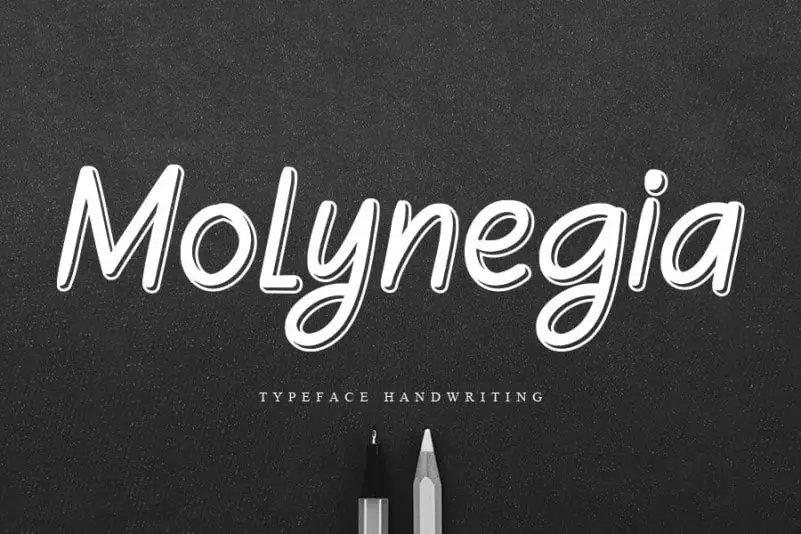
A Molynegia Handwritten Font é uma opção criativa e encantadora para aqueles que buscam um estilo autêntico e elegante na sua designação de texto. Com seu charme natural, essa fonte escrita a mão se destaca em várias aplicações, desde estilos de wall displays até embalagens exclusivas ou cartões de visita. Suas linhas suaves e gestos fluidos fazem-a perfeita para dar um toque especial em publicações nas redes sociais, anúncios, embalagens de produtos, marcas de etiquetas, fotografias, logotipos e até mesmo em impressões finais como água-marinha. Ideal para aqueles que buscam uma fonte escrita a mão que se adapta à vários ambientes e estilos de design, seja para um evento especial ou para aplicar em seu produto mais recentemente lançado. O designer andikastudio criou esta fonte com muito cuidado, levando em conta cada detalhe, o que resulta num recurso gráfico único e elegante. A Molynegia Handwritten Font é uma escolha ótima para quem deseja dar um toque pessoal a suas criações.